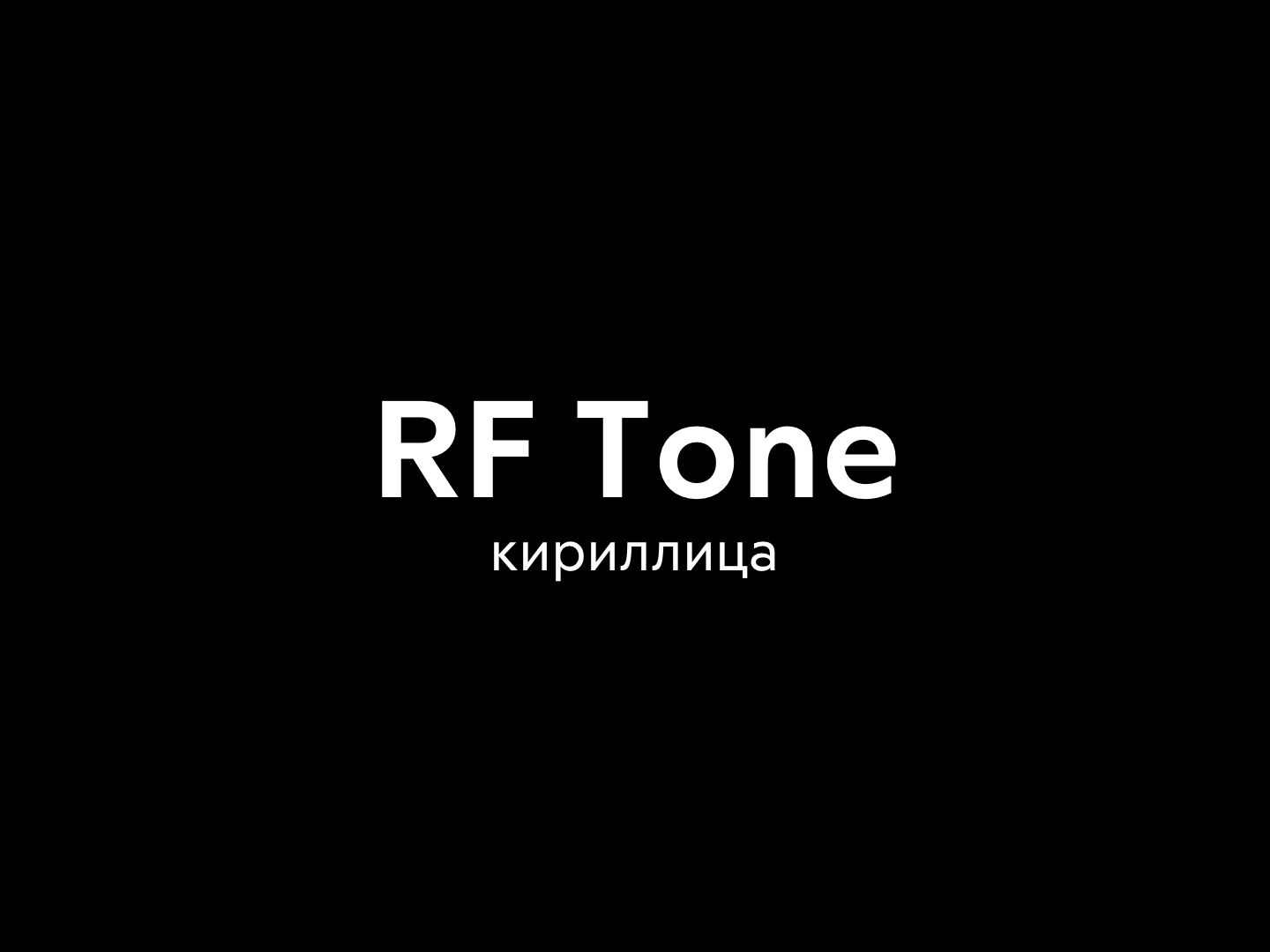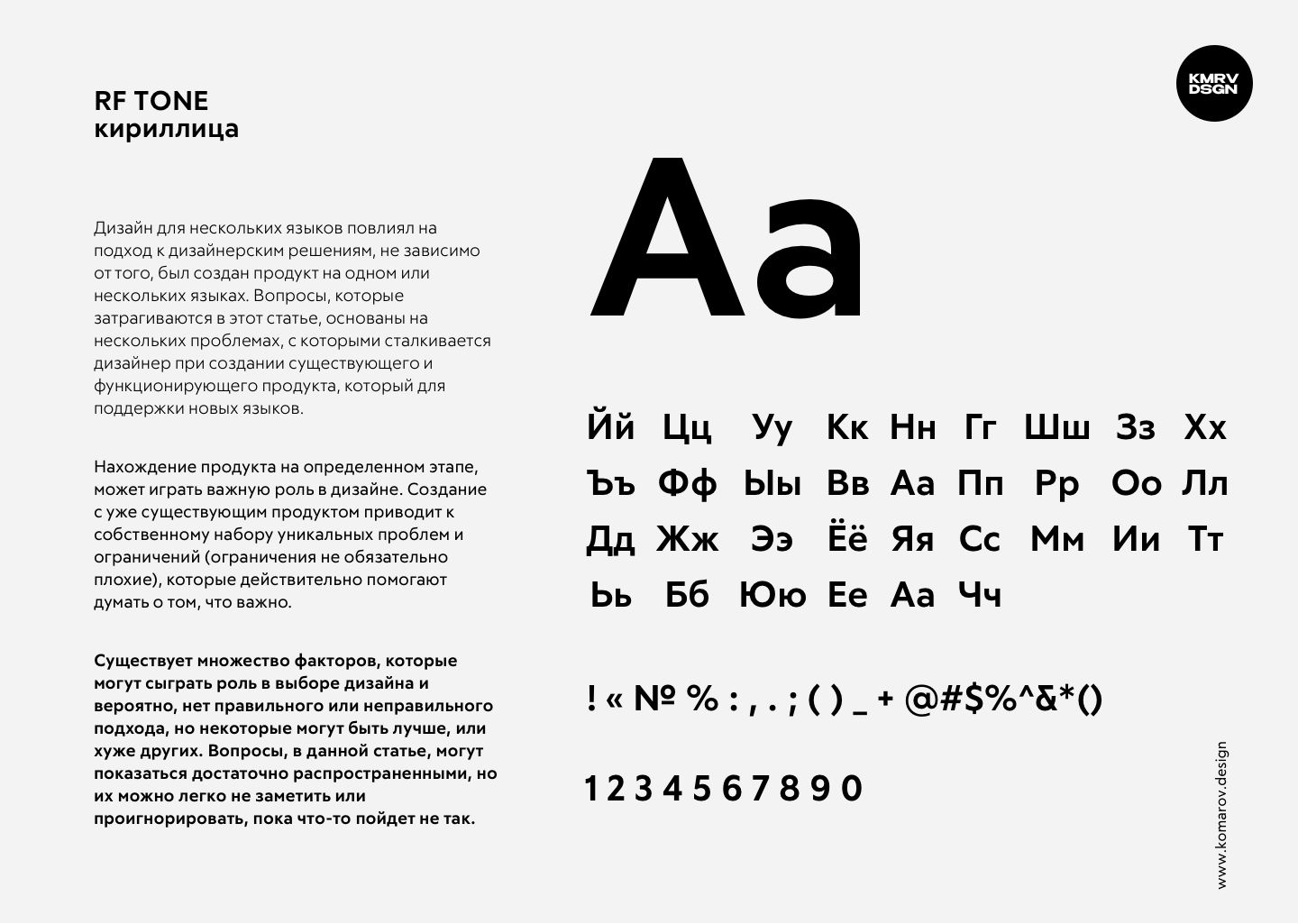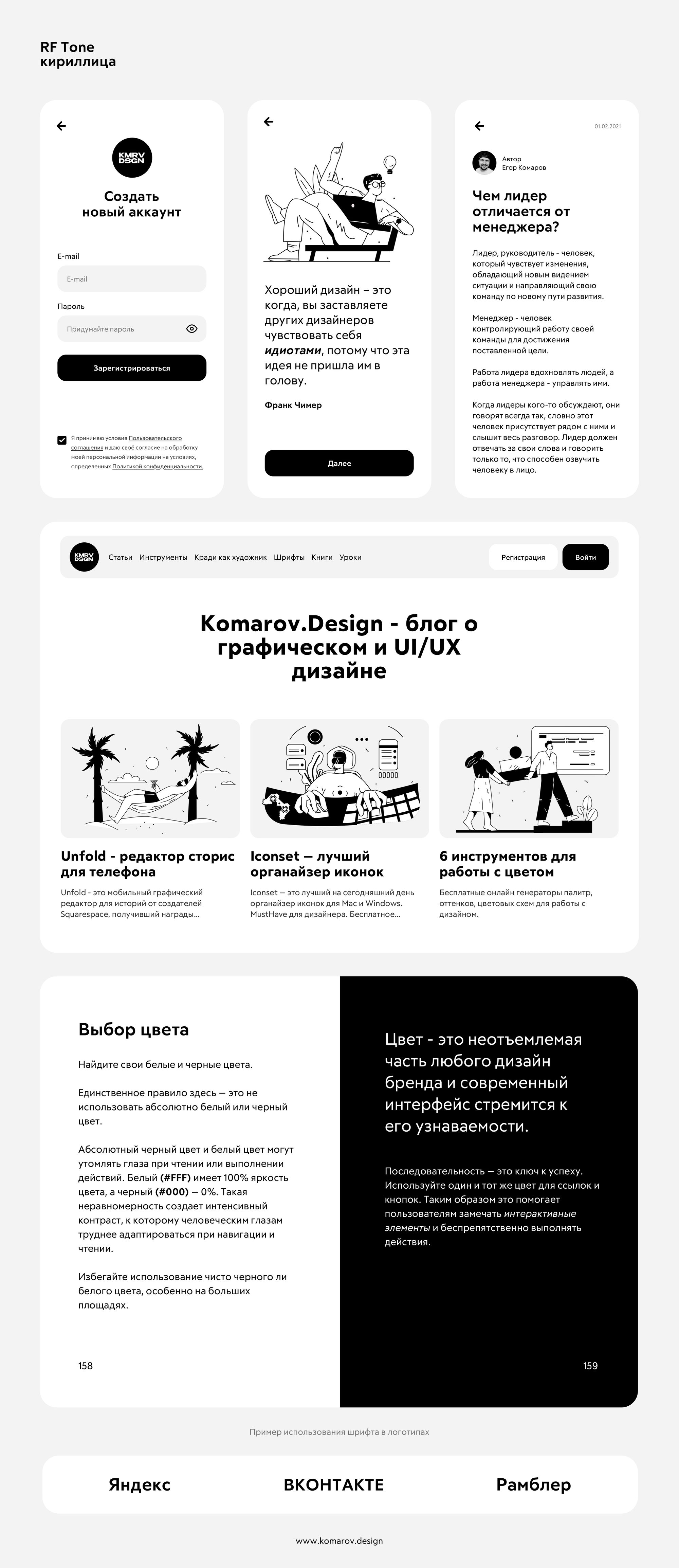
RF Tone шрифт
Шрифт RF Tone удобен для чтения отлично подходит в качестве основного шрифта в дизайне веб-сайтов. Логотипы и брендинг, упаковка, плакаты, музыкальные обложки, видео - это лишь некоторые области, в которых Tone может вам помочь.
RF Tone - это чистый и приятный кириллический шрифт.
Тон был вдохновлен классическими геометрическими шрифтами без засечек, но имеет отчетливый современный дух. Содержит 16 стилей от сверхлегкого до черного: 8 обычных и 8 курсивных. Имеют многоязычную поддержку и большое количество функций OpenType.
Этот шрифт удобен для чтения при небольшом размере. Отлично подходит для больших фрагментов текста или в качестве основного шрифта в дизайне веб-сайтов. Логотипы и брендинг, упаковка, плакаты, музыкальные обложки, навигационные системы, видео - это лишь некоторые области, в которых Tone может вам помочь.